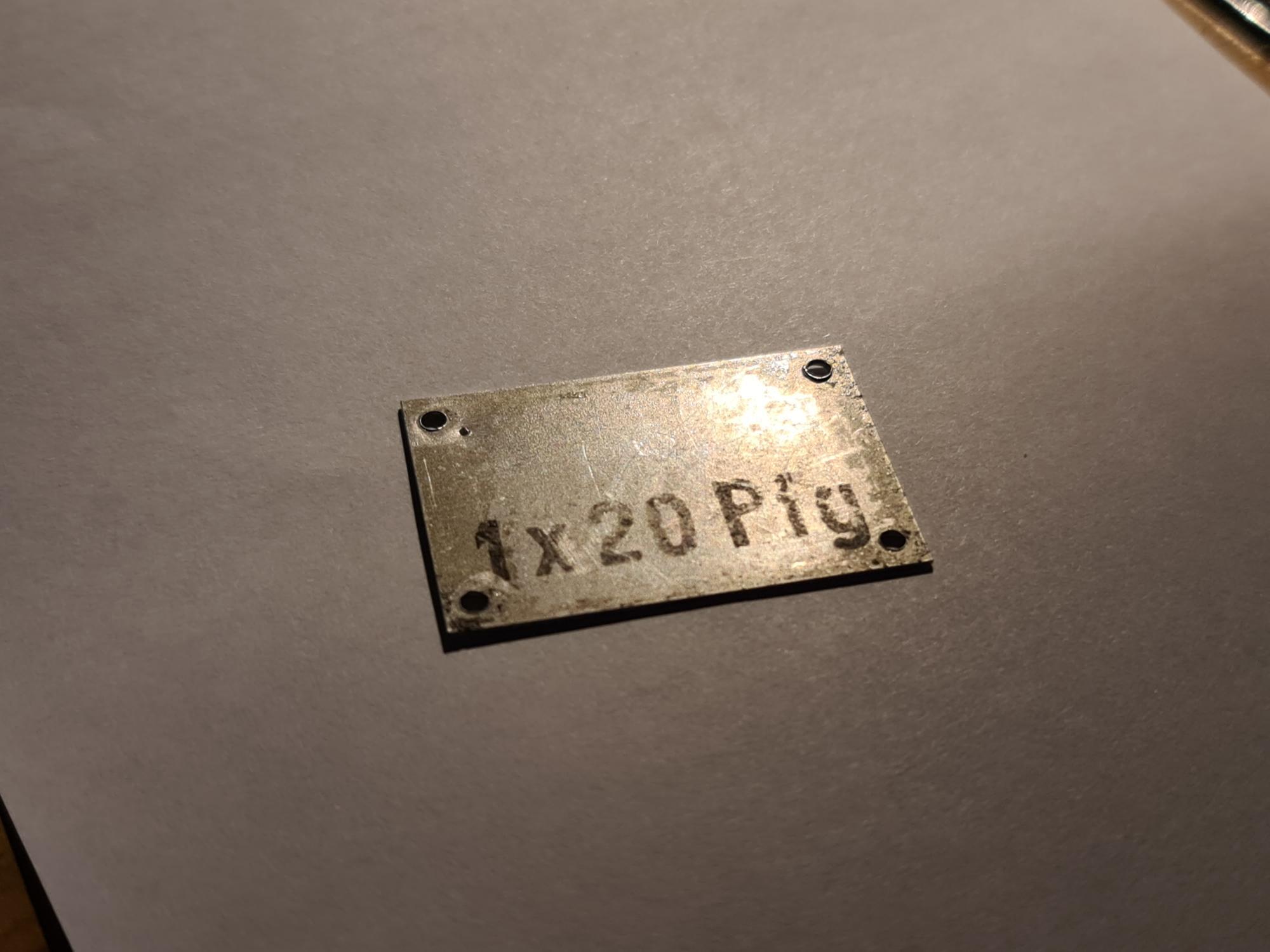
Beschriftung Münztelefon Jahr 1958 - Font gesucht
ich mache gerade ein altes Münztelefon M58b wieder hübsch und habe auf einem Alu-Schild eine verblichene Schrift gefunden,
die leserlich werden  soll.
Auf dem Foto habe ich schräg fotografiert, da damit die Schrift am besten erkennbar ist - von oben gesehen ist sie fast weg.
Ich würde mich sehr freuen, wenn mir jemand helfen könnte die Schriftartart zu finden.
Bisher scheiterte meine Suche an der Spitze der 1 bzw. den Rundungen den 2.